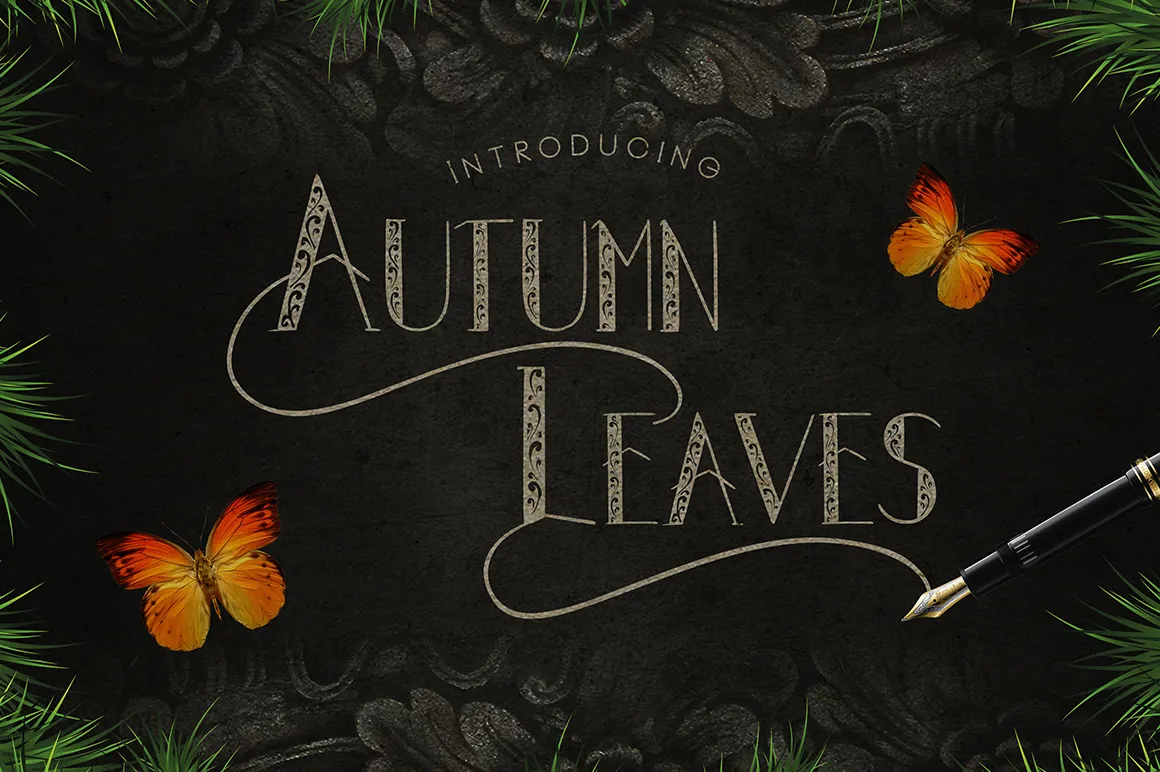
Autumn Leaves é uma fonte tipo vintage inspirada no estilo clássico e antiguamente popular. Esta fonte oferece uma óptima base para criar identidades corporativas, embalagens de produtos, convites, citações e até mesmo posters de propaganda. Ideal tanto para estilos tradicionais quanto para um toque moderno em suas criações. Com o uso desta fonte do madeDuk, você pode dar ao seu design uma cara vintage contemporânea que vai agradar os amantes da literatura clássica e dos estilos antigos. Seja por meio de t-shirts personalizadas ou posters de propaganda criados com esta fonte. Especialmente adequada para usar em elementos do cotidiano, como etiquetas em produtos, Autumn Leaves traz uma pitada de nostalgia ao seu design que é definitivamente o toque perfeito para qualquer projeto. Com o free version disponível, você pode experimentar os recursos desta fonte antes de decidir se quer adquiri-la em sua versão completa. Para obter esta, basta clicar na link abaixo.